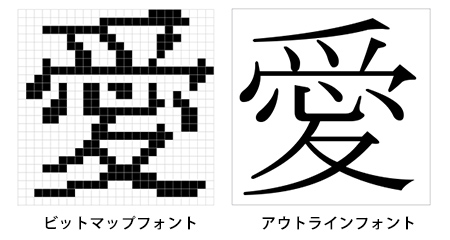
MS ゴシック相当フォント
HGゴシックB
MS 明朝相当フォント
HG明朝L
リコーのフォントは、プリンター開発とともに発展してきました。
インパクトプリンターや電子タイプライター用の活字フォントデザインに始まり、1980年代に登場したパソコンやワープロ用ドットインパクトプリンター向けに ビットマップフォントを制作しました。その後、プリンターや画面の解像度が向上してドット数が増えるにしたがい文字サイズのバリエーションを 増やしていきましたが、ビットマップフォントではデータ容量が小さくて済む代わりに拡大表示すると文字品位が劣化してしまうため、これを克服するためにアウトラインフォントを開発しました。
このアウトラインフォント技術をベースに、MS ゴシック、MS 明朝はWindows® OSで初めての日本語TrueType Fontとして誕生しました。
当書体はWindows® 3.1(日本語版1993年発売)以降、改訂しながら搭載され続けています。